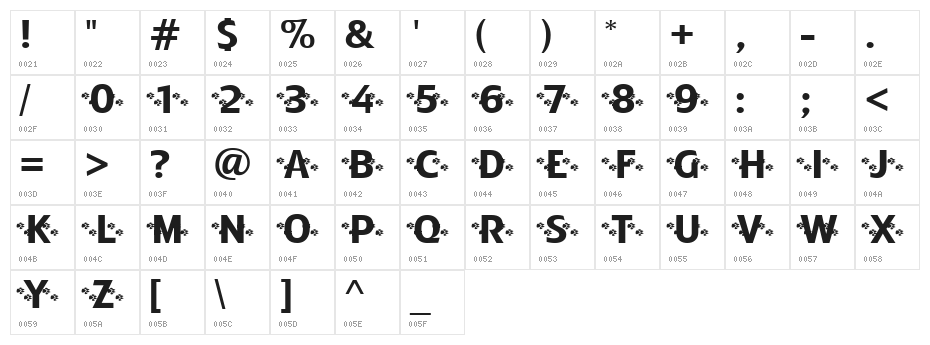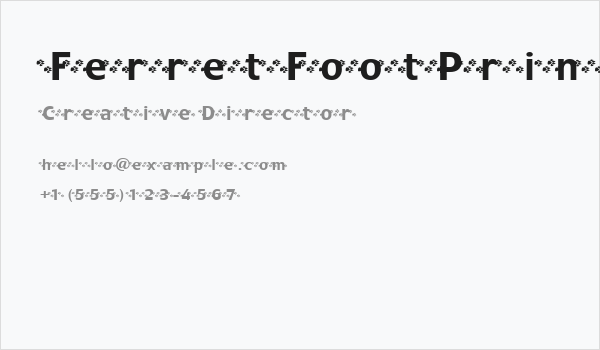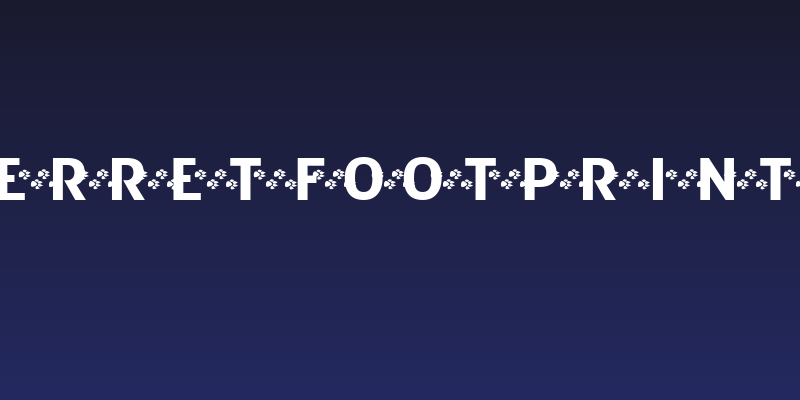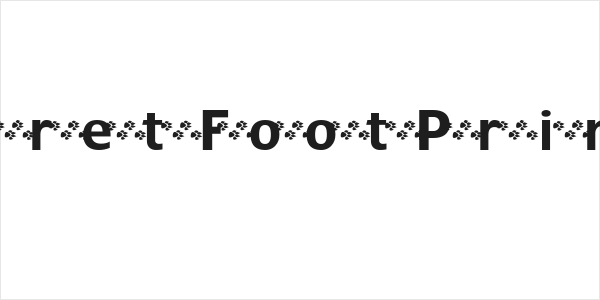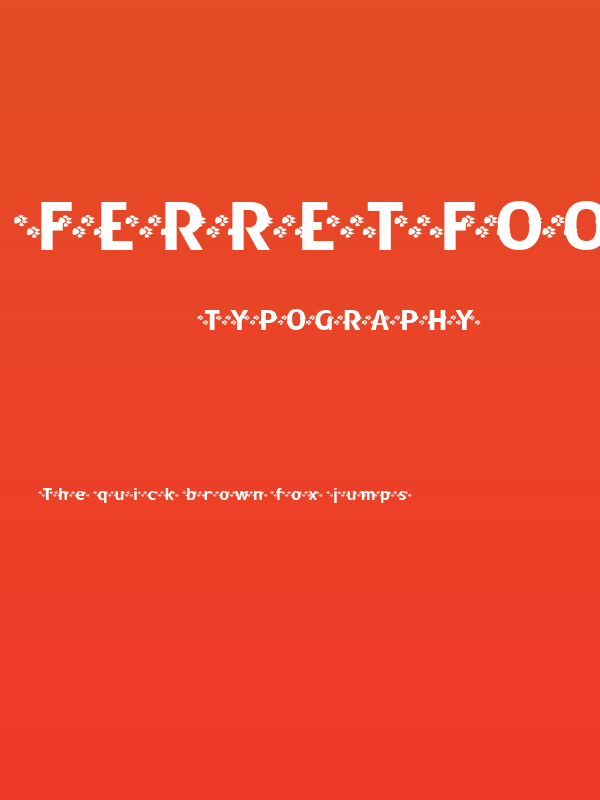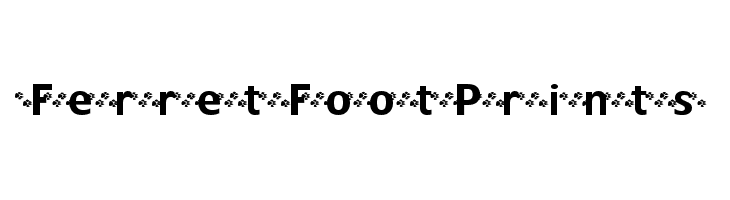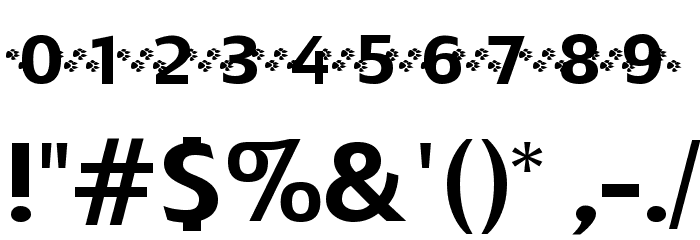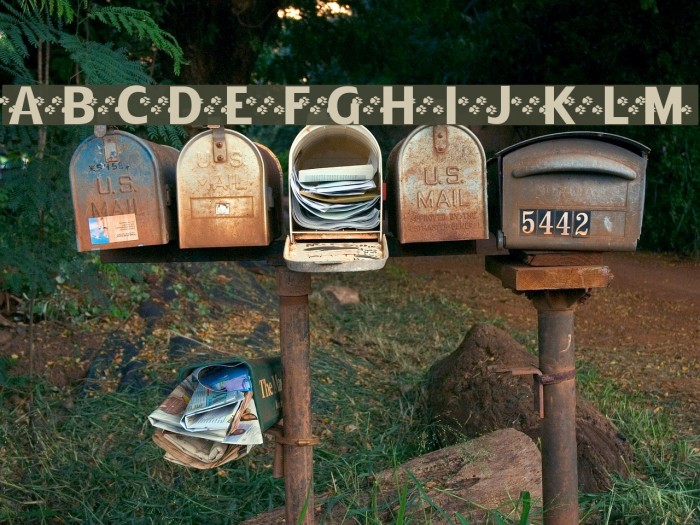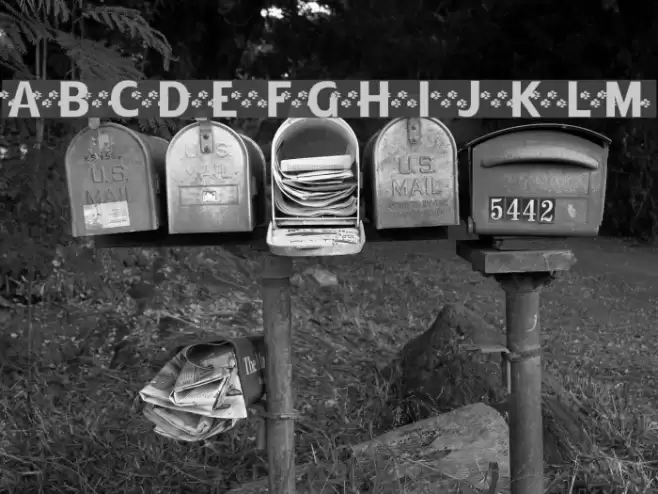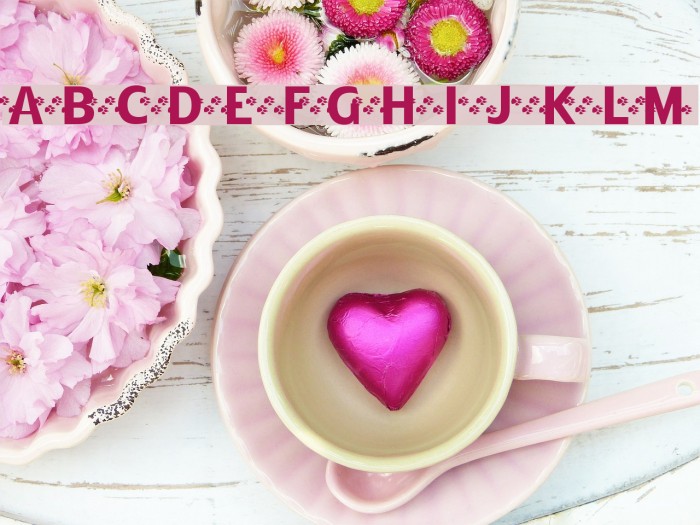
FerretFootPrints Font
| Catégories | Capitals |
| Style général | Playful, Decorative |
| Cas d'utilisation | Headlines, Logos, Invitations |
| Projets proposés | Ideal for children's books, pet-related branding, playful invitations, and novelty items. |